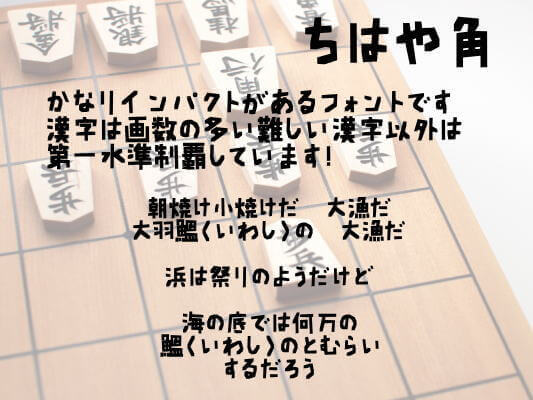
にくまるフォントは、ふっくらした太めの字形とやさしいシルエットが特徴で、子ども向け商品やポップな広告に最適です。親しみやすい雰囲気を演出したいロゴや見出しにもぴったりですよ。
FZゴンタかなは、極太で角ばったデザインが特徴で、下重心のシルエットが安定感を演出します。インパクトを重視したタイトルやロゴ、バラエティ番組の字幕、ポップ広告の見出しに最適です。
コーポレート・ロゴ(ラウンド)は、角に丸みをもたせた太めの線が特徴で、優しい印象を与えます。商品ロゴや企業ロゴ、タイトルや見出しに最適で、親しみやすさと安心感を伝える広告やチラシにもおすすめです。
チェックポイント★リベンジは、極太で無骨なラインと角ばった直線が特徴のフォントです。スポーツチームやアクション系コンテンツのロゴ、ゲームのタイトル画面に最適です。
源ノ明朝は、縦長で上品な骨格とセリフ付きの端正な仕上がりが特徴です。雑誌や書籍の本文、式典資料、ブランドロゴなど、幅広い用途で品のある印象を与えます。
ニコ角フォントは、角ばったモダンなデザインにやや丸みを加えた、視認性の高いフォントです。WEBやアプリのUI、YouTube字幕などに最適で、デジタル広告にもぴったりです。
Nikkyou Sansは、極太で角ばったデザインが特徴のフォントです。直線中心のスッキリした形で、漢字も英語も統一感があります。イベント告知やゲームのロゴ、元気な印象を伝えたいポスターに最適です。
ラノベPOP V2は、太めでインパクトのある字形が特徴で、現代的なデザインが魅力です。和文と欧文の統一感が高く、ポップなチラシやライトノベルの表紙にぴったりです。
新コミック体は、手書き風の自然な曲線とすっきりとした細めの線が特徴です。ブログやエッセイ、雑貨ロゴ、マンガのセリフなど、親しみやすい文章にぴったりです。欧文や記号も整っており、統一感があります。
ニコモジ+(プラス)は、角の丸いモダンなデザインと太めの線幅が特徴で、親しみやすさと近未来感を演出します。ゲーム実況や配信サムネイル、ポップなバナーに最適です。
ちはや角は、ざっくりとした太めの輪郭と手作り感のある線が特徴で、力強さと親しみを両立しています。子ども向け教材や絵本の見出し、お店のPOP、イベントチラシ、動画のテロップなどに最適です。
ちはやゴシックは、手書き風の素朴なタッチと筆記体のような揺らぎが特徴です。丸みを帯びた端と細めの字形が柔らかい印象を与え、ノート風資料やSNS投稿、絵本にぴったりです。
コーポレート・ロゴは、均整の取れたモダンな骨格で信頼感を演出し、資料作成やUIデザインにも最適です。視認性が高く、小さなサイズでもクリアに表示され、柔らかさと親しみやすさを兼ね備えています。
はれのそら明朝は、繊細で優雅な筆の流れを感じる明朝体です。縦横の線のコントラストが美しく、可読性と華やかさを両立しています。結婚式の招待状や女性向けブランドのロゴにぴったりです。
Weedyは、直線と鋭角で構成されたモダンな字形が特徴で、特にテクノロジーや近未来感のあるデザインに最適です。スタイリッシュなイベントのタイトルにもぴったりです。
しまひらがなは、素朴で温かみのある直線的な字形が特徴で、親しみやすさを演出します。子ども向けの絵本や教材、店舗のポップ、ナチュラル系の雑貨デザインにぴったりです。
JKゴシックLは、細身でスマートな印象のゴシック体です。可読性を意識した直線的な造形と、やさしい丸みのある文字端が特徴で、プレゼン資料やコーポレートサイトなど、読みやすさと信頼感を求めるシーンにぴったりです。
ぼくたちのゴシック2レギュラーは、直線的でスッキリとしたデザインが特徴のフォントです。デジタルメディアやUIデザインに最適で、カジュアルなブランドにもぴったりです。
ぼくたちのゴシック2ボールドは、力強い太ゴシック体でありながら、角に丸みを持たせた優しい印象が特徴です。視認性が高く、SNSバナーやイベント告知にぴったりです。
ほのか新アンティーク角は、クラシカルで端正な骨格を持ち、明朝体をベースにした落ち着いた字形が特徴です。文庫本や情報誌、ウェブサイトのUI、フォーマルな文書にも適しています。